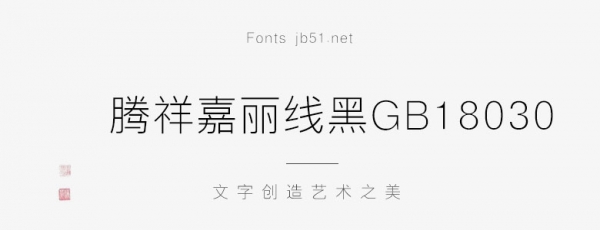
騰祥嘉麗線黑GB18030是一款不錯的藝術(shù)字體,由騰祥字庫出品,字型端正,重心平穩(wěn),布白均勻,適合應(yīng)用于藝術(shù)設(shè)計、平面宣傳設(shè)計、網(wǎng)頁設(shè)計,書法字帖等領(lǐng)域,需要的朋友可以前來本站下載。
騰祥嘉麗黑體系列字庫為騰祥公司早期自行開發(fā)的傳統(tǒng)黑體字庫。字體風(fēng)格采用橫豎筆畫無襯線裝飾的設(shè)計,融入英文設(shè)計元素。字型端正,重心平穩(wěn),布白均勻。此款字體為騰祥嘉麗黑體系列中纖細一款,橫豎筆畫等粗,故取名線黑。